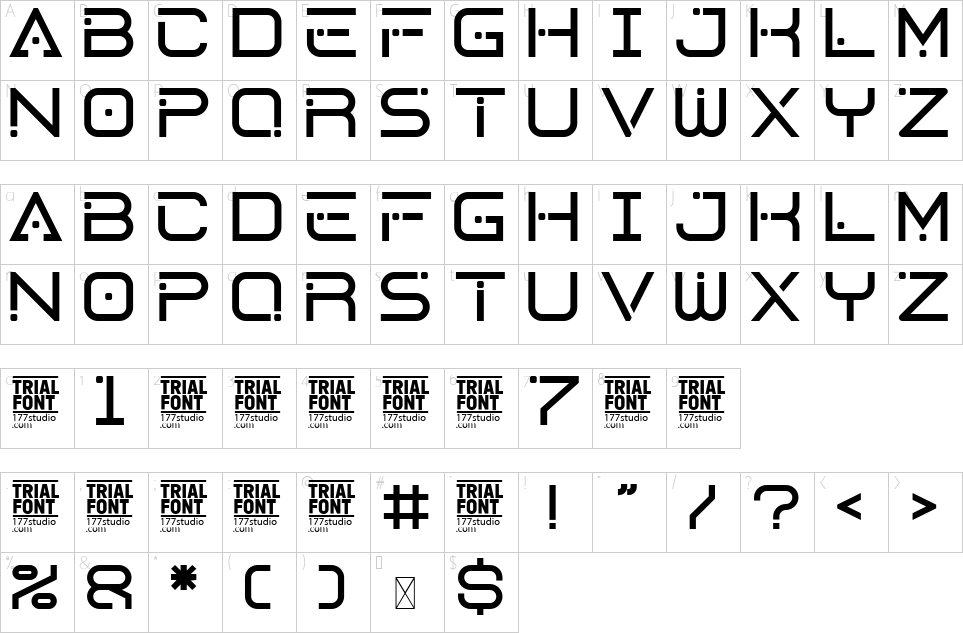
Greatest General Font – 1001 Free Fonts – Fonte Grátis
Greatest General Font - 1001 Free Fonts
A fonte ‘Greatest General Font – 1001 Free Fonts’ é uma seleção diversificada de letras gratuitas que inclui várias opções para aprimorar seu design editorial, gráfico ou digital. Esta fonte foi cuidadosamente criada pela equipe dedicada da 177Studio.com e tem se destacado por sua capacidade de ser usada em diferentes ambientes digitais sem perder qualidade. Com mais de 2 mil downloads, é uma opção confiável para designers, freelancers ou estudantes que buscam fontes robustas e limpas. Combinando um estilo elegante com recursos práticos, a ‘Greatest General Font – 1001 Free Fonts’ oferece uma vasta seleção de letras, adequadas para uso em textos, headlines, aplicações gráficas, e muito mais. A sua liberdade de usar esta fonte sem custo adicional é um benefício que a torna não só uma opção economica, mas também uma alternativa altamente valorizada à fontes pagas, especialmente para ambientes onde o orçamento está limitado.